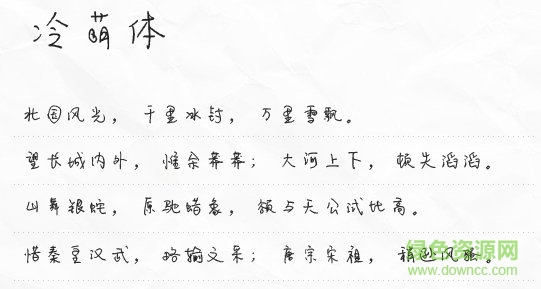
冷萌體是一款硬筆書法制作的手寫字體,字跡淡雅而簡潔,給人嬌小穩(wěn)重的藝術美感,讓你的作品擁有不同的詮釋,綠色資源網(wǎng)誠意推薦!
冷萌體字體是一款適合鋼筆書法書寫的字體,結(jié)構(gòu)完整,沒有中規(guī)中矩的嚴肅,自稱一派,讓人體驗生動有趣的視覺呈現(xiàn)!
冷萌體是有著個性風格的書寫字體,下筆細膩而沉穩(wěn),給人簡潔、不拖沓的干練體驗,同時文字清晰辨識度高,可以廣泛使用在藝術設計、平面設計、包裝設計、海報設計等領域!